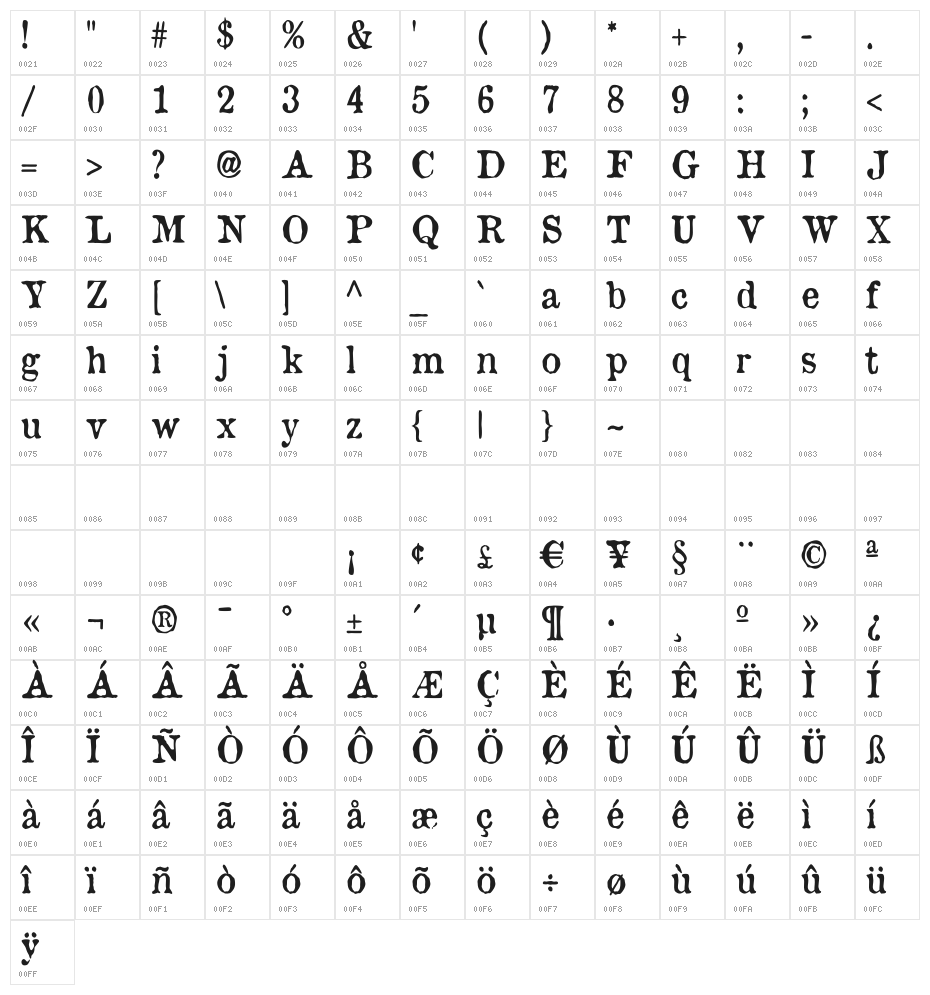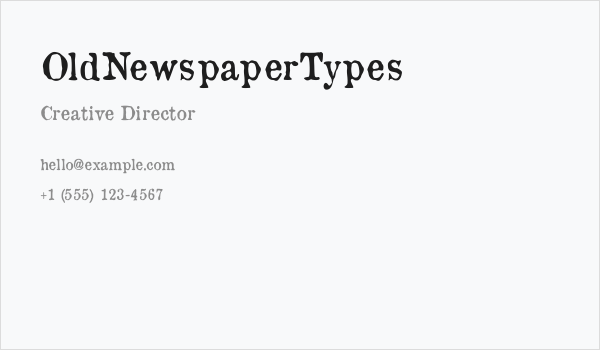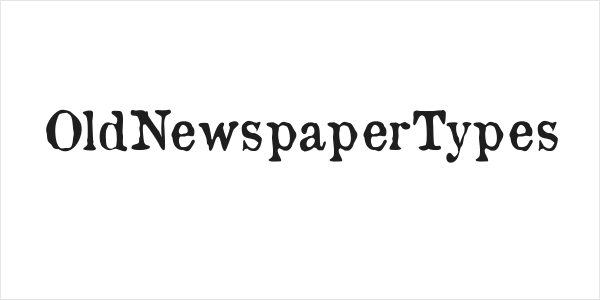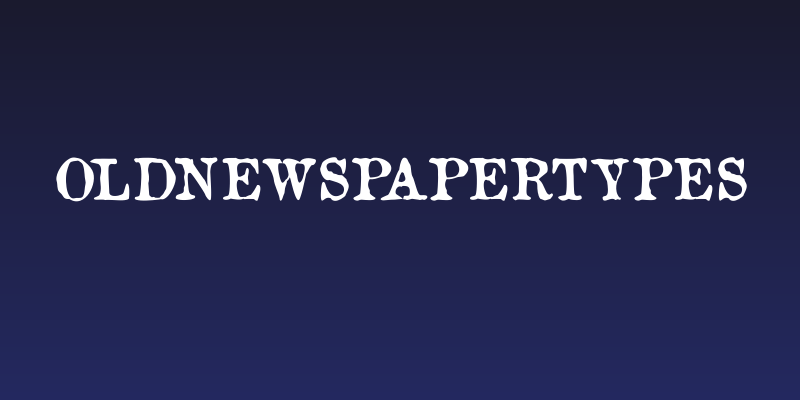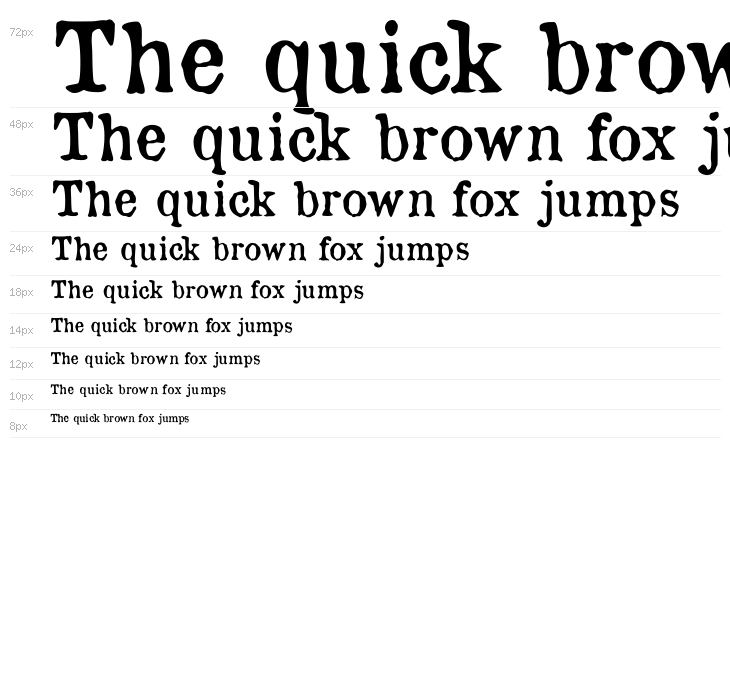
OldNewspaperTypes Font
✎ Typewriter
| 分类 | Typewriter |
| 整体风格 | Vintage |
| 推荐项目 | Ideal for vintage-themed posters, historical publications, retro branding, and any design that seeks to capture an old-world charm. |